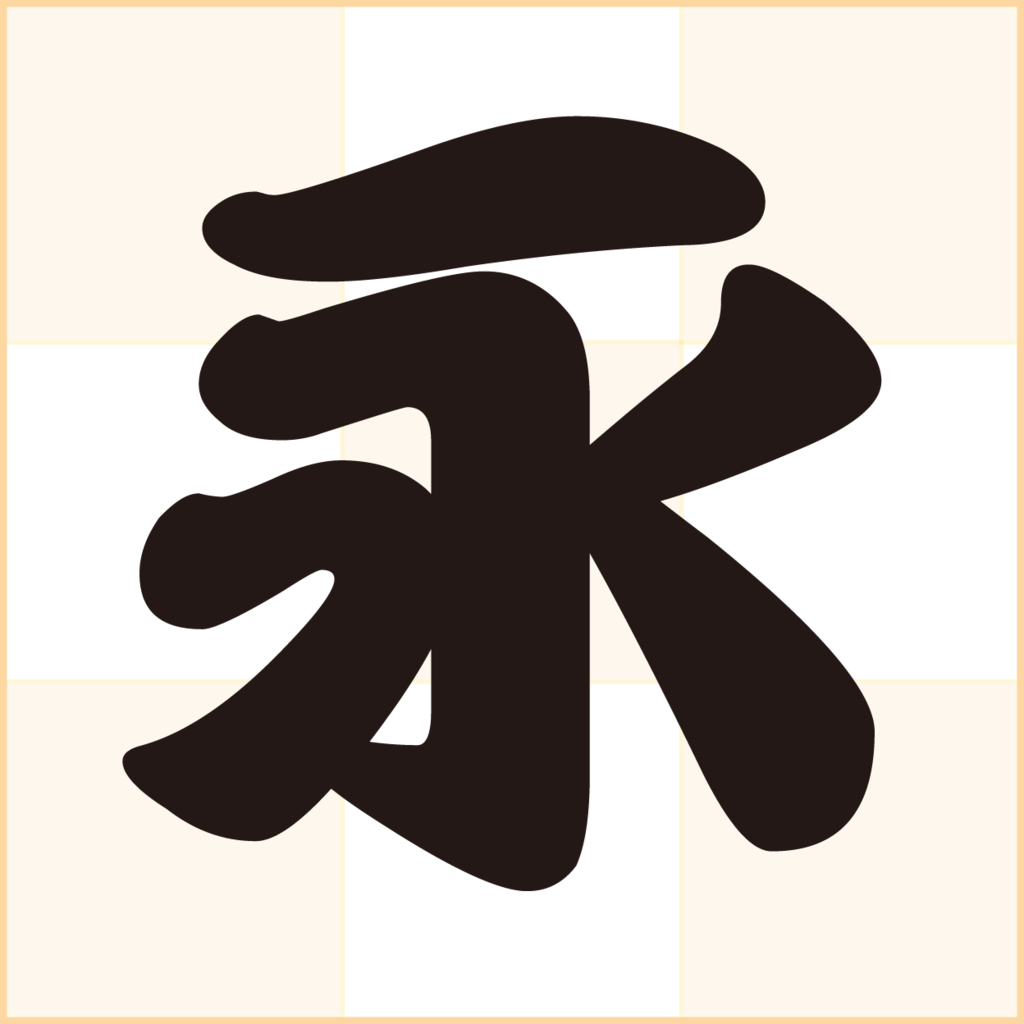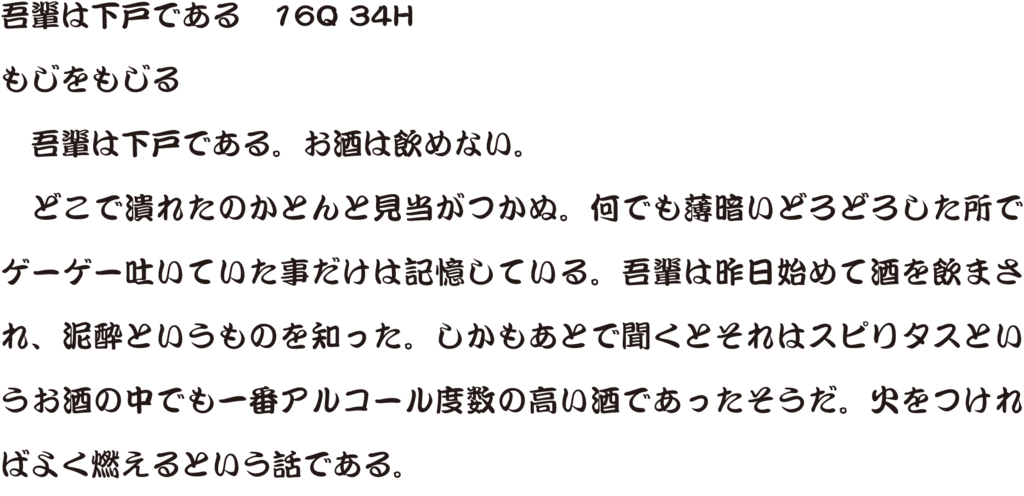
江戸文字「芝居文字(勘亭流)」/ダイナフォント勘亭流
江戸時代に使用された図案文字である通称、江戸文字の一種。通称、勘亭流。
歌舞伎の看板、番付に使用される書体。
書体はダイナコムウェアが開発・販売している勘亭流フォント「DF勘亭流」。
芝居文字(勘亭流)フォント・DF勘亭流の組見本(W6)
新元号「令和」の勘亭流書体見本
新元号「令和」の勘亭流の書体見本。
芝居文字(勘亭流)フォント・DF勘亭流の使用例
太鼓の達人 Nintendo Switchば~じょん!にダイナフォント勘亭流が採用
バンダイナムコエンターテインメントが2018年7月19日に発売した、Nintendo Switch用大人気和太鼓リズムゲーム「太鼓の達人 Nintendo Switchば~じょん!」のゲーム画面などにダイナフォント勘亭流などが採用されている。